人民郵電出版社の中華人民共和国郵電部編『標準電碼本(修訂本)』。1983年発行、定価0.60元。201ページ。この「電碼」とは、電報で中文をやりとりするための文字コードのこと。個々の漢字を4桁の数字*1に対応させている。詳しくは Wikipedia の記事を参照。
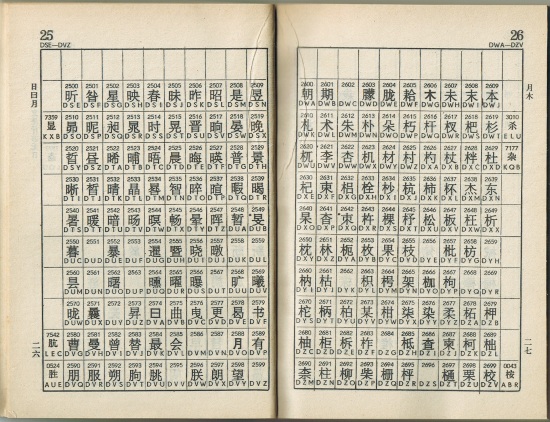
上の画像は、前半(上編)の電碼表。電碼順に漢字が並んでいる。本来は《電碼順=部首順(同一部首の中では画数順)》となっていたのだが、1981年の修訂で追加・削除・字体変更(繁体→簡体)が行われたため、綺麗な並びにはなっていない。歯抜けもある。
例えば、左ページの上中央にある「时(2514, DSS)」。最初に制定されたときは「時」で日部6画だったので、「…晁時晃…」とこの位置に入れられていた。簡体では「时」となって画数が変わるが、修訂では字形を入れ替えただけで位置は変えなかったため、日部6画の中に3画の「时」が交じっている。
同じ行の左端には「显(7359, KXB)」がある。元の字は「顯」で頁部14画だったのが、簡体では「显」(日部6画)となって部首が変わってしまった。しかし、「时」と同じように字形を入れ替えただけで位置はそのままなので、「显」を引こうとして日部の中を探したとしても、このままでは見つけることができない*2。これを避けるために、部首の変わった漢字は(変わった後の部首・画数の)周囲のマス*3に載せてある。
けどいくら工夫したって画数はアテにならんし、正直言って使いにくいよね、ということで、修訂本では後半(下編)にピンイン順の電碼表がついている。
ピンインのアルファベット順に並べられ、その中で①②③④☉(第1〜4声および軽声)の声調別に分かれている。ただ、こちらは英字3桁の符号が併記されていない。小さい活字で印刷されているのは繁体字で、対応する簡体字の後に並んでいる。